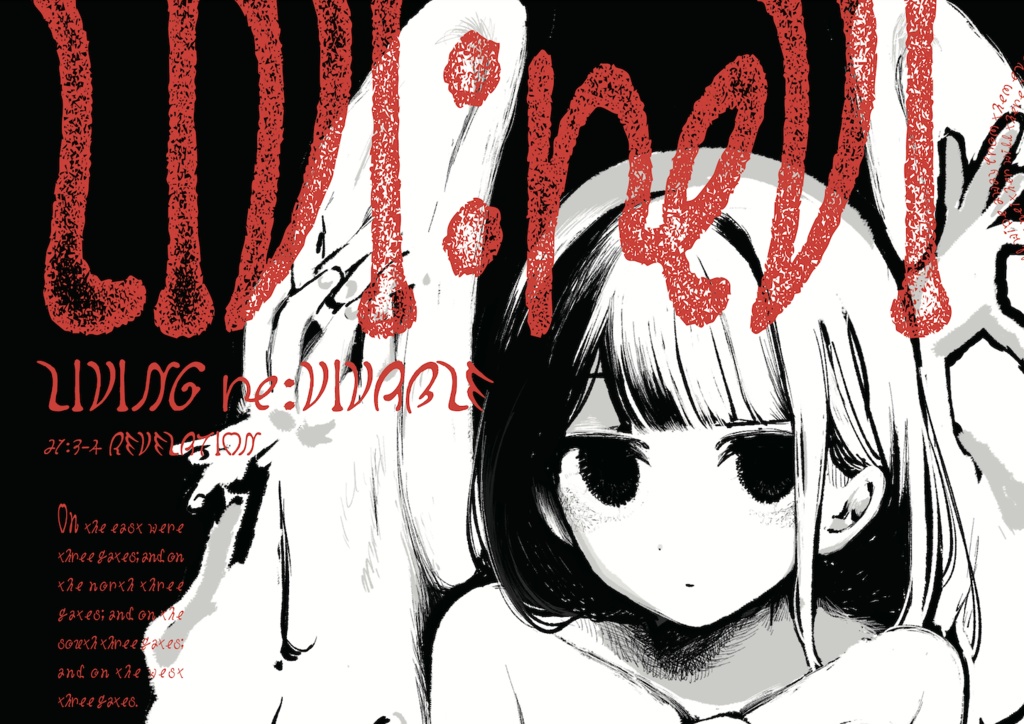
Wing_font
※本フォントのDLは無料で行なっていただけます。 滑らかなエッジやカールが特徴の欧文フォントです。 フォントをインストールして頂くと、ワープロ、グラフィックソフトなどの アプリケーションでこのフォントを使って自由にデザイン、印刷することができます。 ■ご使用に際して■ 初のフォント制作なのでカーニングの不均衡や、下部の読み取りが切れたままフォント化されている文字が数個あるなど様々な欠陥が見られます。そちらをご承知の上DLを行ってください。 (機会があれば作り直すかもしれません) 商用利用可能です。 ■免責事項■ フォントの使用について、いかなる保証も行いません。 発生したいかなる損害(データ損失等を含む)についても、提供側は責任を負いません ■製作者Twitterアカウント■ 魚(ギョ) @GyowaQ 最終更新日 2025/05/15